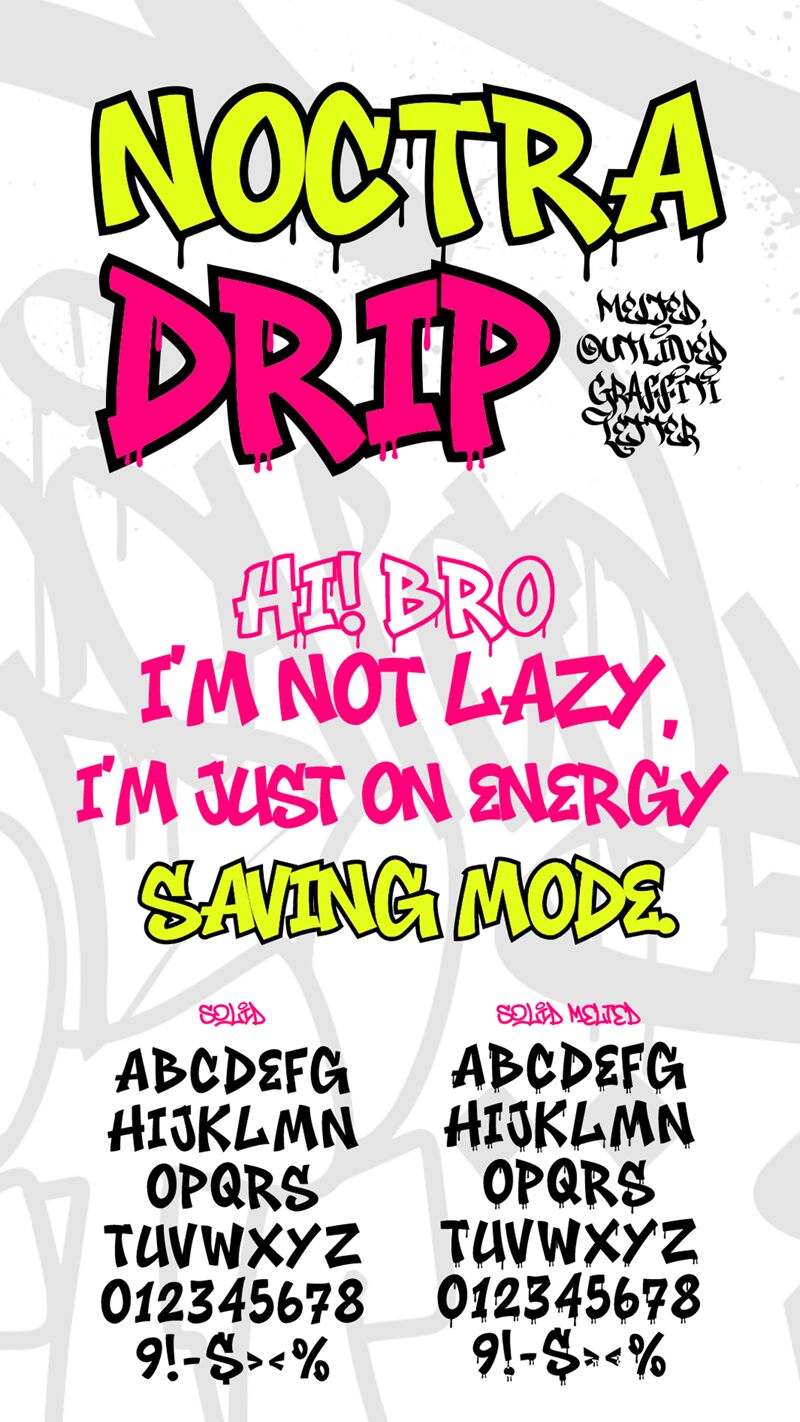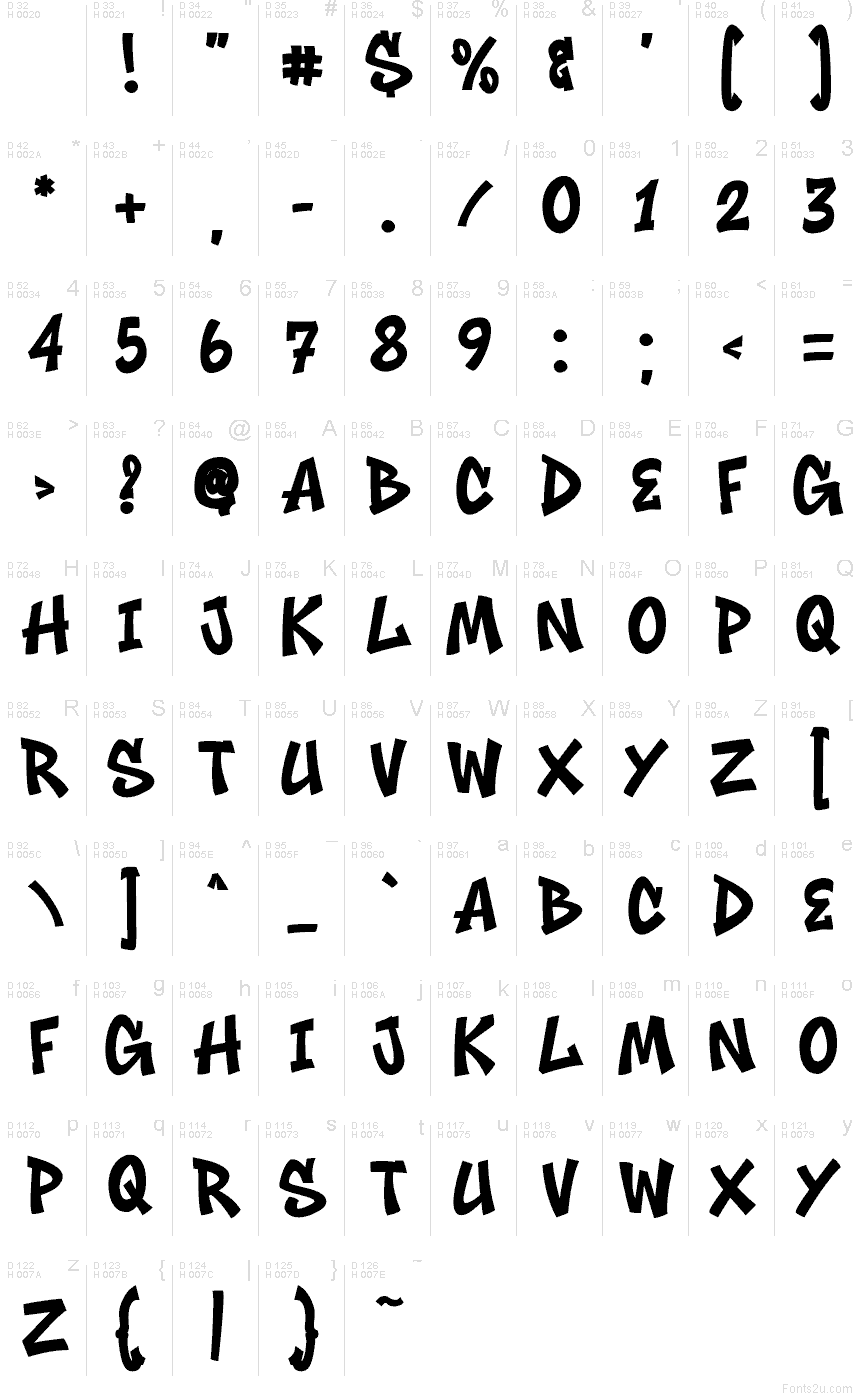
Noctra Drip Solid Solid
Il font Noctra Drip Solid di Muhammad Panji Ramdhani di Figuree Studio porta in vita la famiglia Noctra Drip con tratti spessi e densi, che sembrano spruzzati con una mano sicura e decisa. Le lettere restano audaci e leggibili, mentre i bordi tremolanti e le piccole gocce di vernice aggiungono quell'energia fresca da street art. Noctra Drip Solid è un font graffiti gratuito che dà il meglio di sé quando gli si lascia spazio nei corpi più grandi.
Noctra Drip Solid è perfetto per loghi streetwear, locandine musicali, grafiche da skate, miniature YouTube, copertine di album, sticker e volantini di eventi che richiedono un tocco di grinta immediato. Abbina questo font gratuito a una sans serif condensata pulita per i testi secondari e mantieni la spaziatura leggermente aperta, così che gli schizzi non soffochino il tuo messaggio.